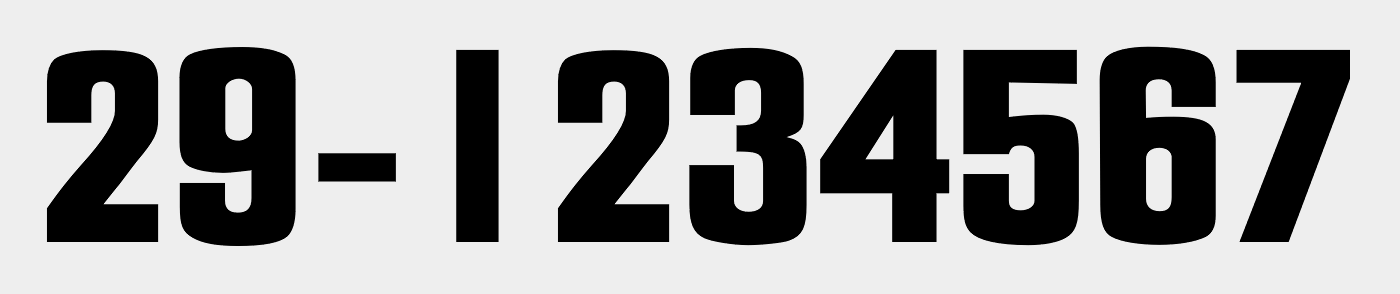
Schrift vom alten Hausnummerschild gesucht
ich suche schon eine recht lange weile und finde nichts annähernd ähnliches, kann mir hier vielleicht jemand helfen...?
finde ich auch recht eigenartig, bin allerdings wirklich verliebt...
soll für alte industriehallen zehn nummernschilder machen und die schrift auf dem schild (zufällig im www drübergestolpert) geht mir nicht mehr aus dem kopf...
diese schmalen einbuchtungen bei der eurostyle mag ich überhaupt nicht...